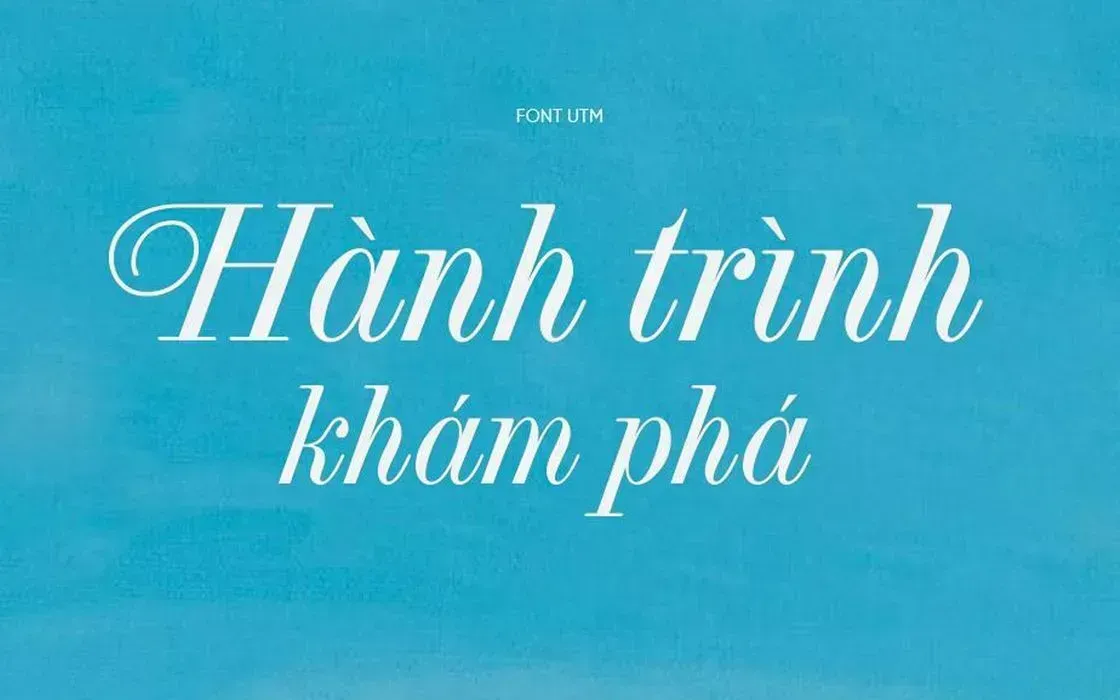
UTM French Vanilla là một kiểu font serif (có chân) mang phong cách cổ điển pha chút lãng mạn, nổi bật với các đường nét mềm mại, thanh lịch và nhẹ nhàng như chính cái tên “Vanilla” gợi lên. Font sử dụng các chân chữ tinh tế, kết hợp giữa nét dày và nét mảnh một cách hài hòa, tạo cảm giác cao cấp nhưng không quá cứng nhắc.
Từng ký tự trong UTM French Vanilla có sự bay bổng nhẹ, thích hợp cho các thiết kế cần truyền tải vẻ sang trọng, nữ tính và có chiều sâu thẩm mỹ. Đây là font lý tưởng để dùng trong thiết kế bao bì mỹ phẩm, logo thời trang, ấn phẩm thương hiệu cao cấp hoặc tạp chí chuyên đề.
Font gốc French Vanilla Serif được phát triển bởi Arterfak Project – một studio thiết kế font nổi tiếng đến từ Indonesia, chuyên tạo ra các kiểu chữ kết hợp giữa cảm hứng hoài cổ và ứng dụng hiện đại.
Nếu bạn đang tìm một font chữ có chân vừa sang trọng vừa tình cảm, phù hợp với các thương hiệu nữ tính hoặc thiết kế có yếu tố hoài niệm, thì UTM French Vanilla là lựa chọn hoàn hảo để mang lại cảm giác tinh tế và dễ mến cho người xem.